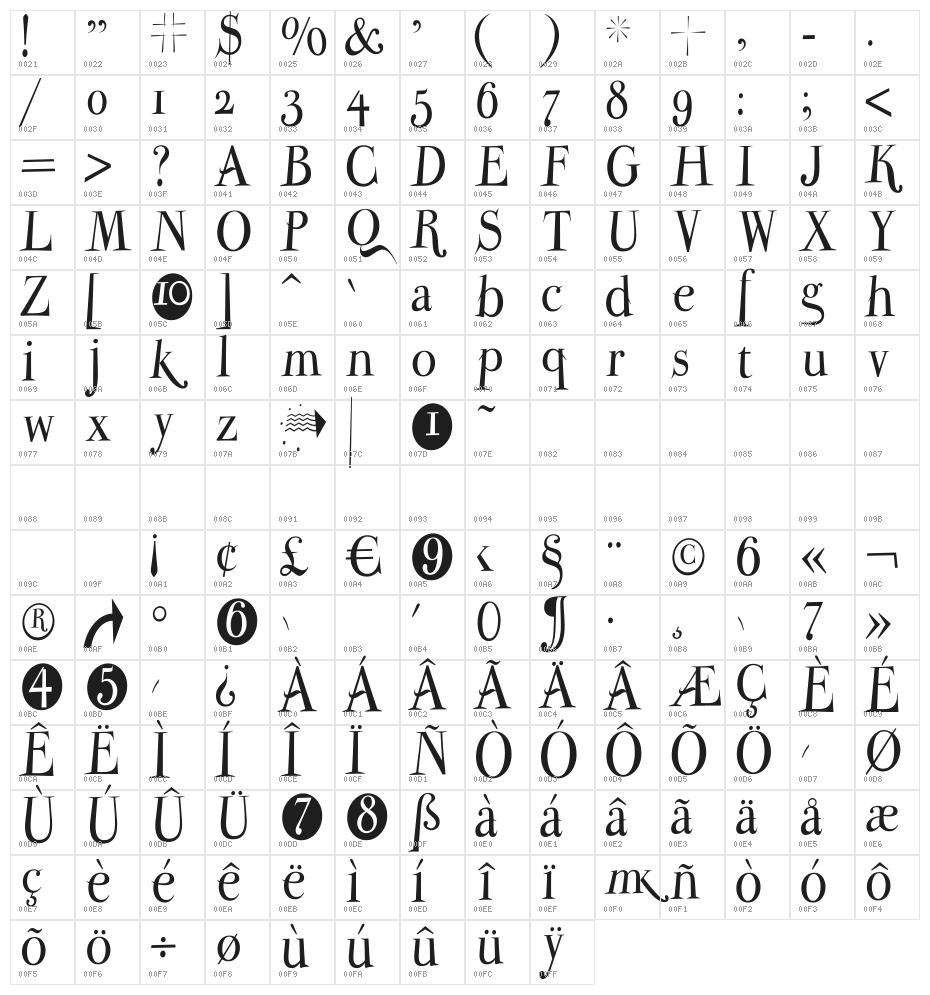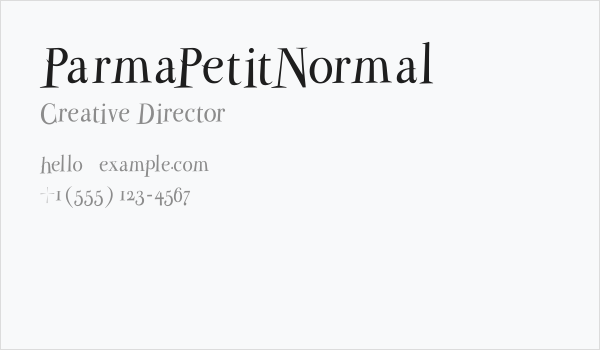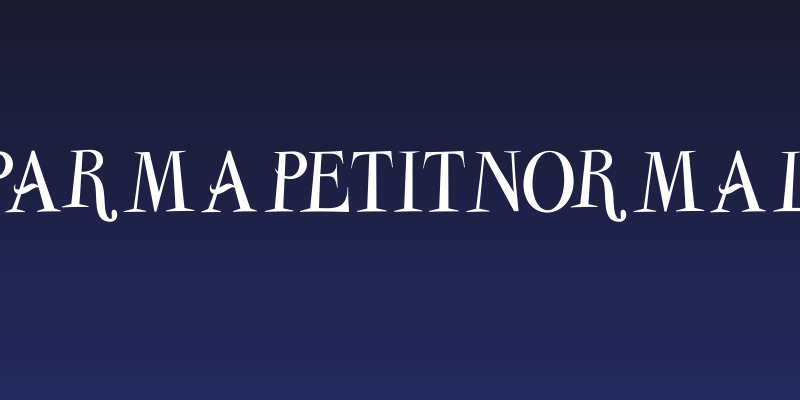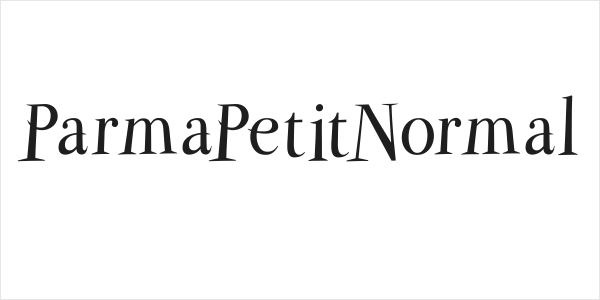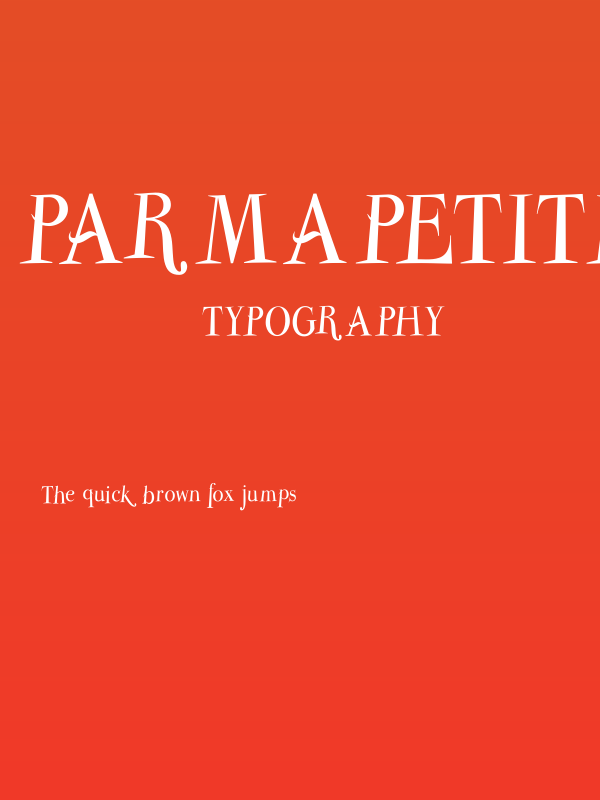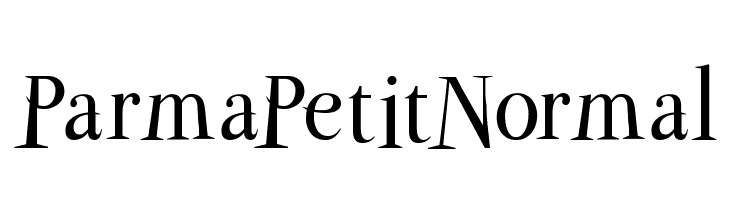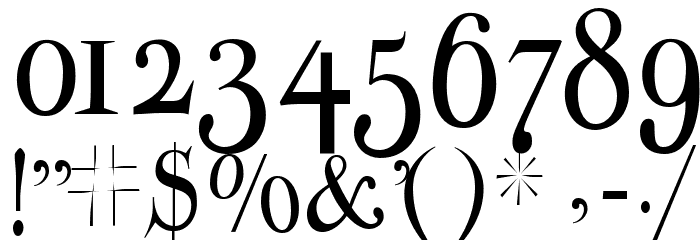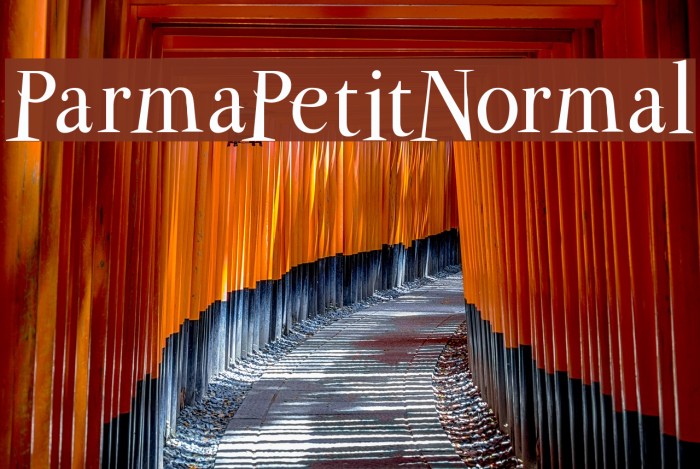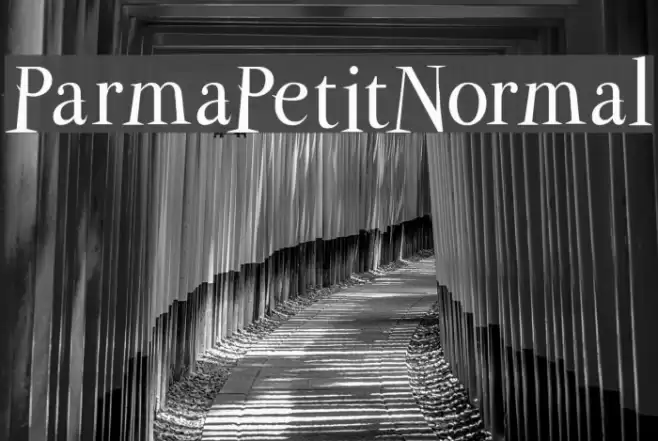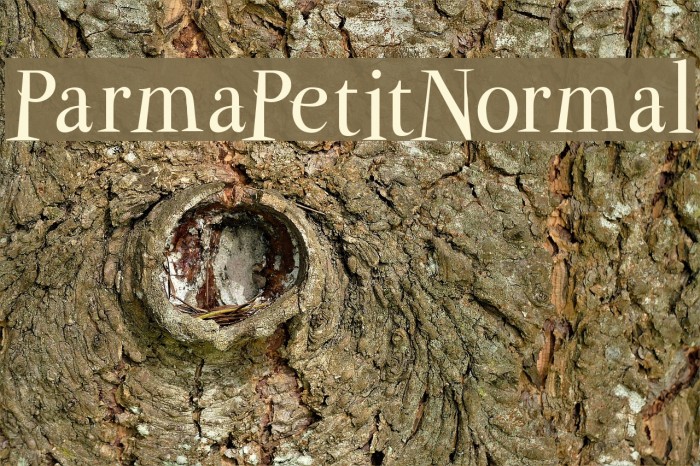
ParmaPetitNormal Font
| कंट्रास्ट | High |
| समग्र शैली | Classic |
| उपयोग का मामला | Headlines, Body text, Logos |
| सुझाए गए प्रोजेक्ट | Ideal for book covers, invitations, branding projects, and editorial design where a touch of elegance is desired. |